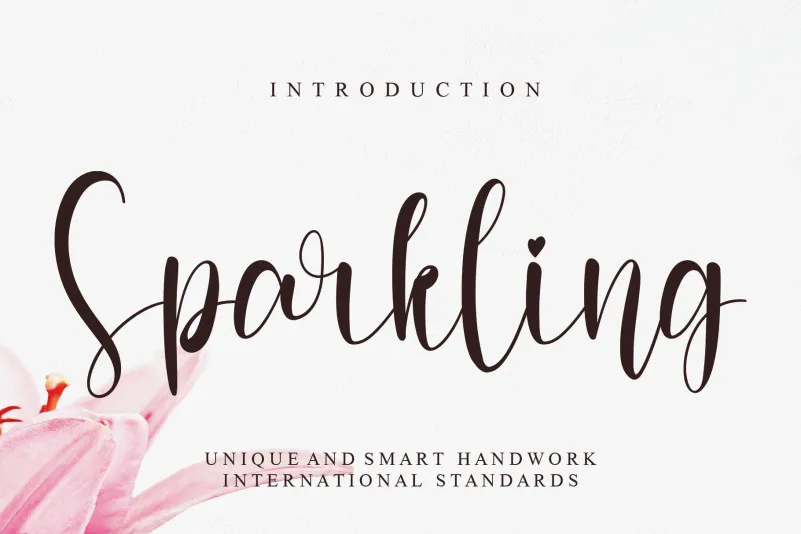
Sparkling Font – Download Grátis
Esta fonte escrita à mão é atrativa e divertida, com seus personagens meticulosamente cuidados. É perfeitamente adequada para uma variedade de projetos, desde marcos criativos e fotografias até rótulos ou cartões de visita. Seu estilo levemente desenhado faz dela uma escolha ideal para designers em busca de um toque único e interessante para seus trabalhos. Com ‘Sparkling Font’, a escrita ficará ainda mais especial, seja ela usada em textos informativos, design gráfico ou em qualquer outro projeto que você possa imaginar. Uma vez que sua elegância se combina perfeitamente com um toque de personalidade, está pronta para tornar seus projetos ainda mais memoráveis e atraentes.